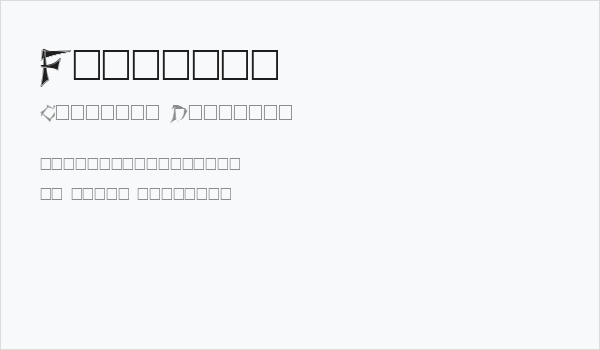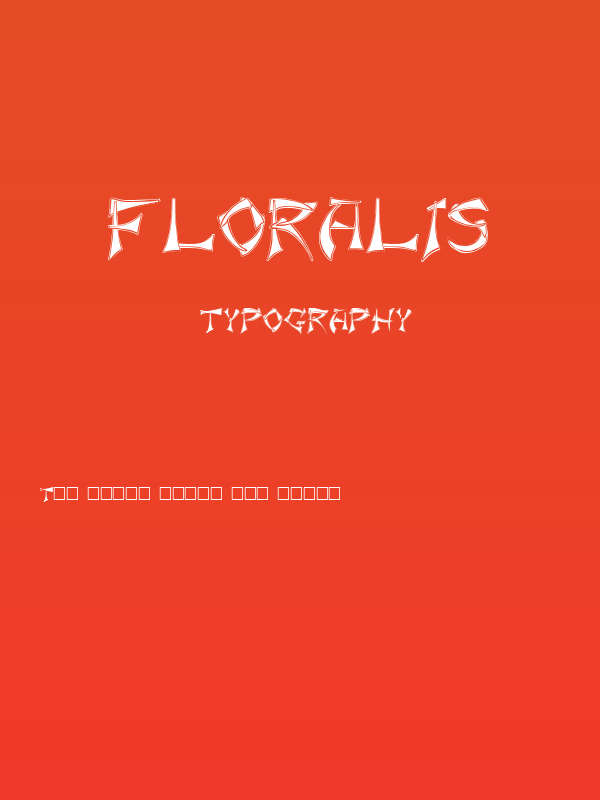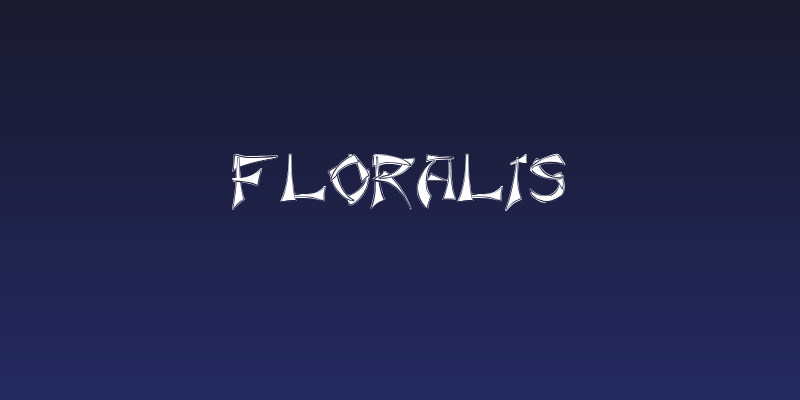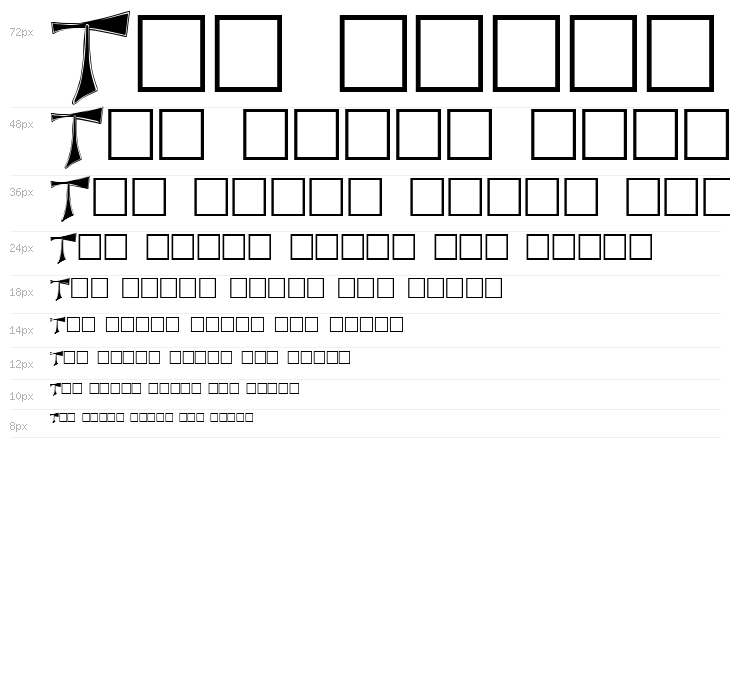
Floralis Font
✎ Asian
| 分类 | Asian |
| 使用场景 | Logos, Headlines |
| 推荐项目 | Ideal for fantasy book covers, medieval-themed event invitations, or artistic posters. |